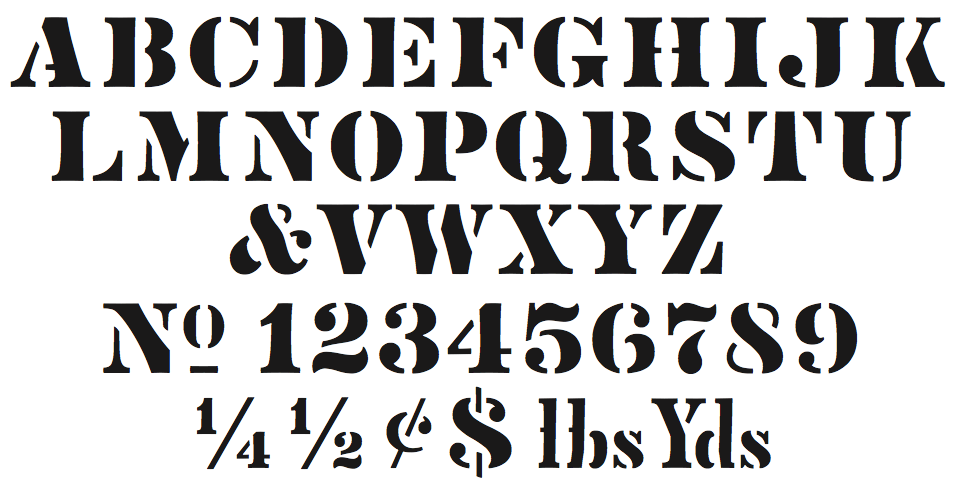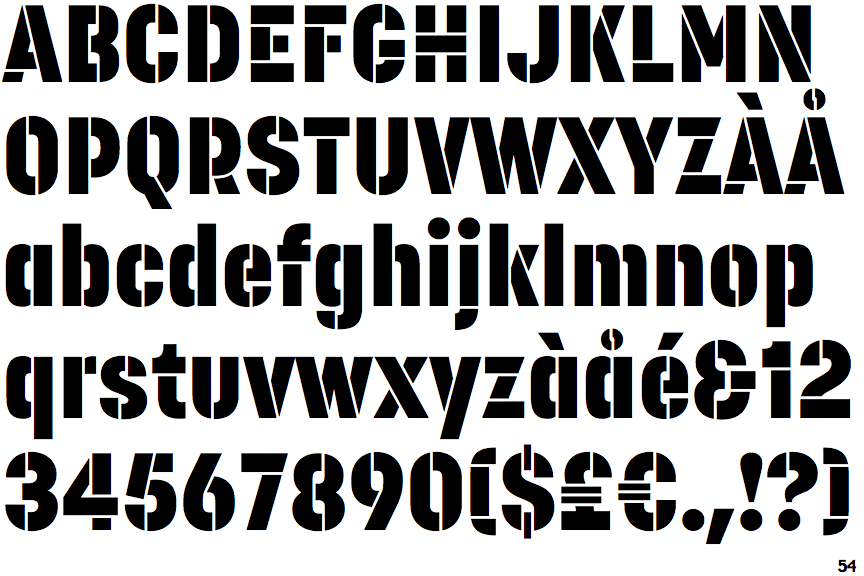
Трафаретные шрифты для номеров, надписей и эмблем АТП
Считаем целесообразным представить несколько наиболее популярных и близких к аутентичным трафаретных шрифтов, которые могут быть использованы в качестве надписей к эмблемам АТП, маркировке грузов и т.д. при изготовлении масштабных моделей. При выборе варианта покраски модели автобуса рекомендуем следовать требованиям из ГОСТ 24348-80 , который регламентирует порядок нанесения цветографических схем на городские автобусы и автобусы дальнего следования. Также желательно ознакомиться с рекомендациями по нанесению эмблем и номеров , где указаны их точные размеры, место расположения и требования к применяемым цветам согласно картотеки ЛКМ .
Образец трафаретного шрифта Sunline Trafaret.
Образец трафаретного шрифта Aero Matics Stencil.
Образец трафаретного шрифта Danger.
Образец трафаретного шрифта Depot Trapharet 2D.
Некоторые примеры использования трафаретных шрифтов представлены в нашей коллекции реальных прототипов эмблем АТП , предприятий и ведомств времен СССР, наносившихся на транспортные средства различного назначения.
Трафарет «Испытания» на маршрутном указателе ЛАЗ-699А «Карпаты» Опытный II.
Трафарет отрисован с маршрутного указателя оригинальной фотографии автобуса ЛАЗ-699А «Карпаты» Опытный II . Файл трафарета с прозрачным фоном лежит . Любителям скрупулёзного создания моделей придется закрасить перемычки в букве «ы» (в экспериментальном цеху ЛАЗа, по видимому, с этой буквой были проблемы).
Шрифт из стандарта ГОСТ 14192-96
Ещё один популярный, но зачастую неверно используемый среди моделистов шрифт — из документа
Отличается он одинаковой шириной букв и цифр, а также закругленными окончаниями элементов букв.Шрифты тип 1 и тип 2 из ГОСТ 14192-96.
Шрифт тип 3 из ГОСТ 14192-96.
Образец трафаретного шрифта ГОСТ 14192-96 (тип 3).
Ниже представлен растровый образец шрифта надписей и цифр из Государственного стандарта РФ
Более ранний ГОСТ Р 50574-93 был введен в действие 01.01.1994 взамен ГОСТ 21392-90 и также содержал образец шрифта, который находился в обязательном «Приложении В», там же были приведены образцы надписей «ГИБДД» и «ДПС» (выполнены более толстым шрифтом).
ГОСТ Р 50574-2002 достаточно большой по объему информации, тем не менее, рекомендуется для ознакомления коллекционерам и создателям масштабных моделей, поскольку содержит примеры цветографических схем и расположения надписей на транспорте всех видов оперативных служб. Кстати, документ ссылается на всё ещё действующий ГОСТ 19715-74 (введен в действие 30.06.1975), которым регламентируются форма и размеры эмблемы Красного Креста. Эта маркировка наносится на материальные средства медицинской службы, в том числе и на санитарные автомобили и специальные средства транспорта. Одним из таких ранних спецсредств был санитарный ЛАЗ-695Б — автобус для перевозки раненых, созданный львовянами в 1959 году в качестве опытного образца.
Возможно, данный шрифт уже был отрисован энтузиастами, однако, нам пока найти не удалось.
Трафарет — это специальное приспособление, которое используют для нанесения одинаковых букв и цифр на большое количество поверхностей. Трафарет может быть простым листом из бумаги, пленки или другого удобного для вырезания материала, в котором прорезаны сквозные отверстия нужной формы. Через эти отверстия проходит красящее вещество и составляет общую картину.
Для начала, вам потребуется выбрать шрифт для трафарета. В принципе, вы можете использовать любой шрифт для своего трафарета. Однако учтите, что в таком случае, при вырезании трафарета вам нужно будет продумать саму конструкцию, в которую должны входить перемычки. Это желательно сделать для букв у которых есть замкнутые контуры. Такие буквы как О, А, Д и тд, должны быть выполнены с перемычками, иначе их внутренние части будут залиты сплошным цветом. Иногда это не критично, но для общей картины, желательно делать с внутренними пустотами.
Вот, к примеру один из шрифтов, латинские буквы которого не имеют замкнутых контуров. Название шрифта «Bauhaus 93». Но в примере я не буду использовать этот шрифт. Хотелось бы вспомнить, как выглядели старые советские трафареты. Найти шрифт такого трафарета в интернете не составит труда. Для тех кто не хочет лишний раз напрягаться, вот ссылка для скачивания. Сам шрифт называется «Trafaret Kit Transparent». Видимо создатель этого шрифта сам родом из СНГ или России.
Braunstein — это трафаретный шрифт с классическим дизайном, который лучше всего подходит для дизайнерских проектов в стиле ретро, включая упаковку продуктов, значки, футболки, вывески и многое другое. Шрифт имеет ручной дизайн, который добавит естественности вашему дизайну.